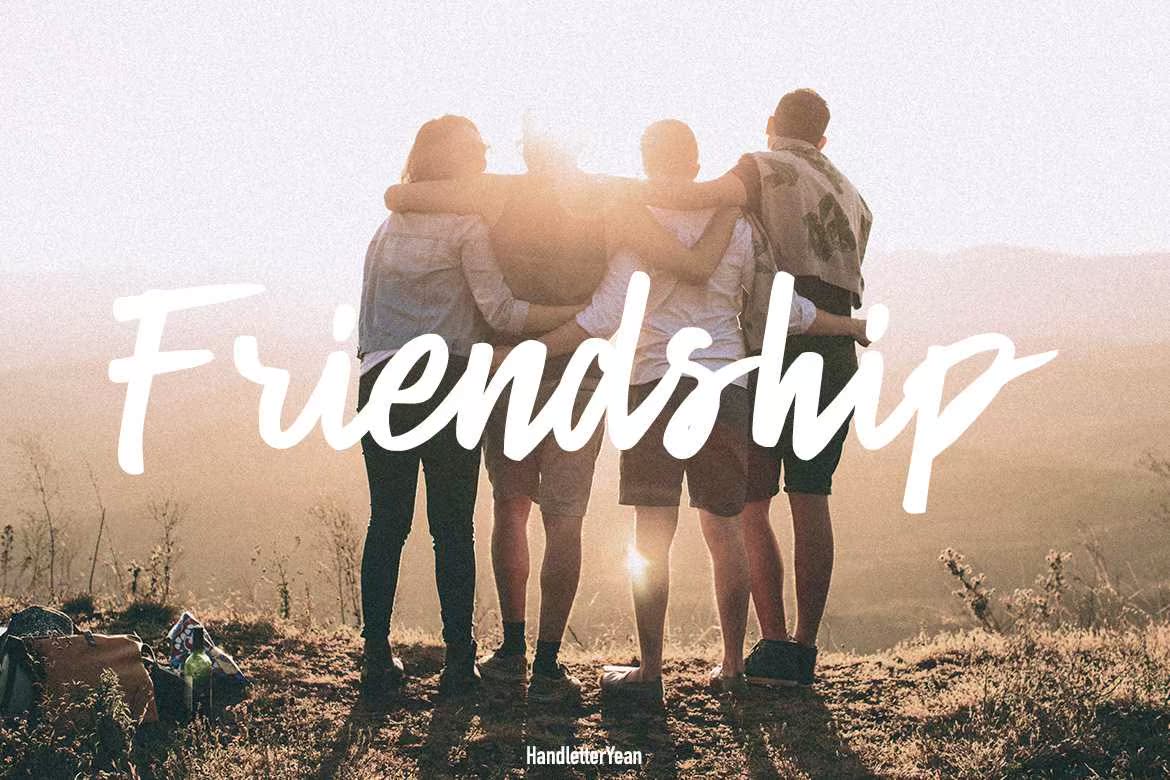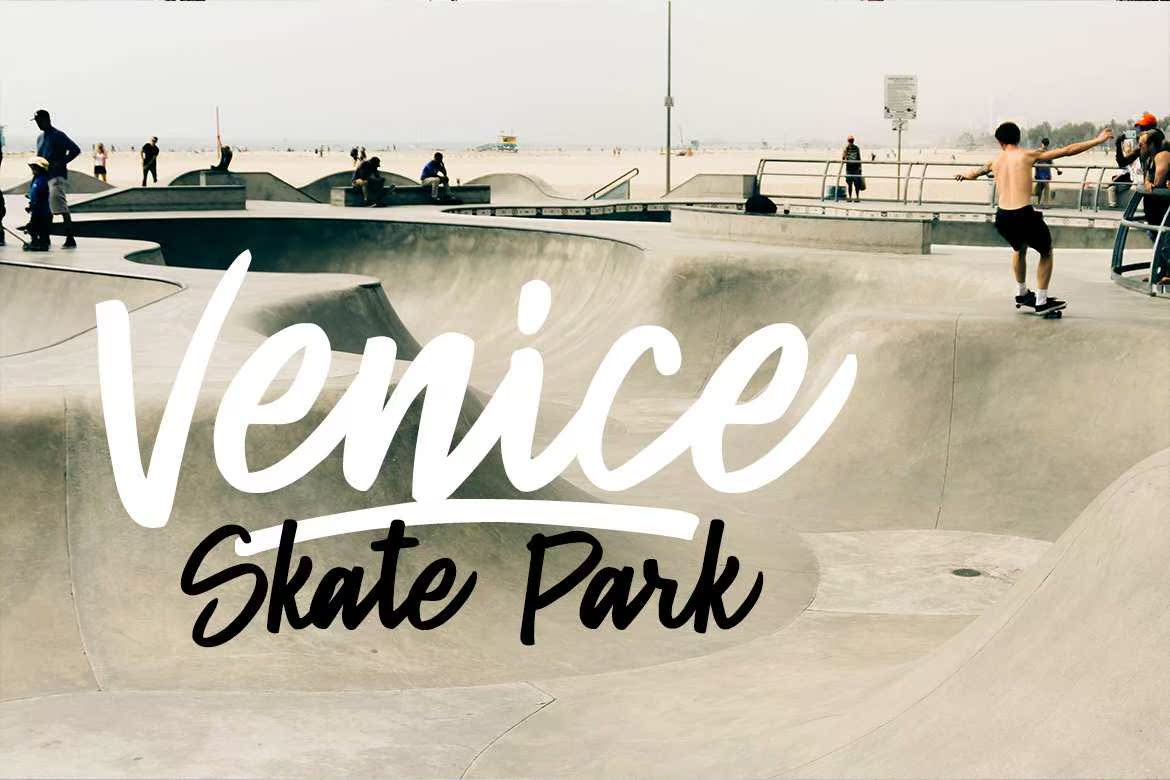
Helio来自Handletyean,是一种简单的手写画笔字体。它包含大写字母、小写字母、标点符号和符号。Helio非常适用于海报、徽标、包装、品牌、杂志、报价、标题、广告、名片、标志、迎宾卡、传单、服装等等!Helio来自Handletyean,是一种简单的手写画笔字体。它包含大写字母、小写字母、标点符号和符号。Helio非常适用于海报、徽标、包装、品牌、杂志、报价、标题、广告、名片、标志、迎宾卡、传单、服装等等!